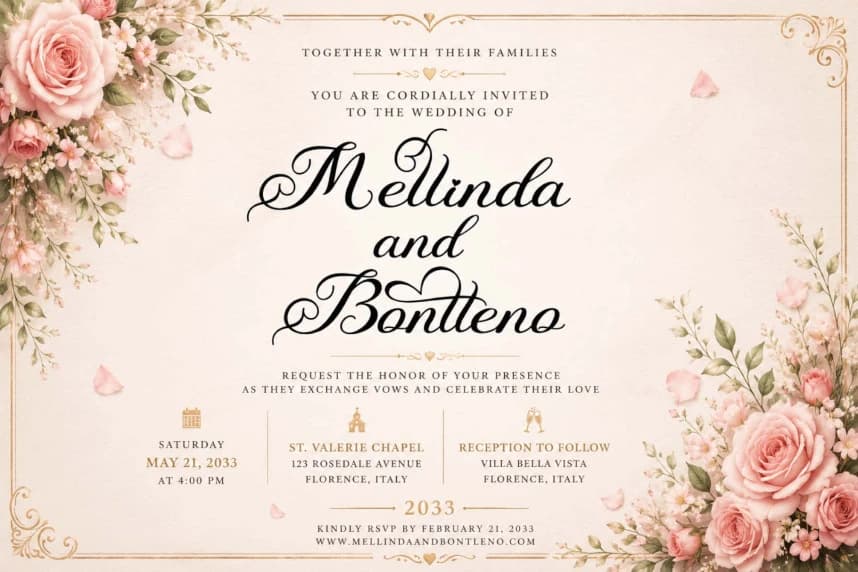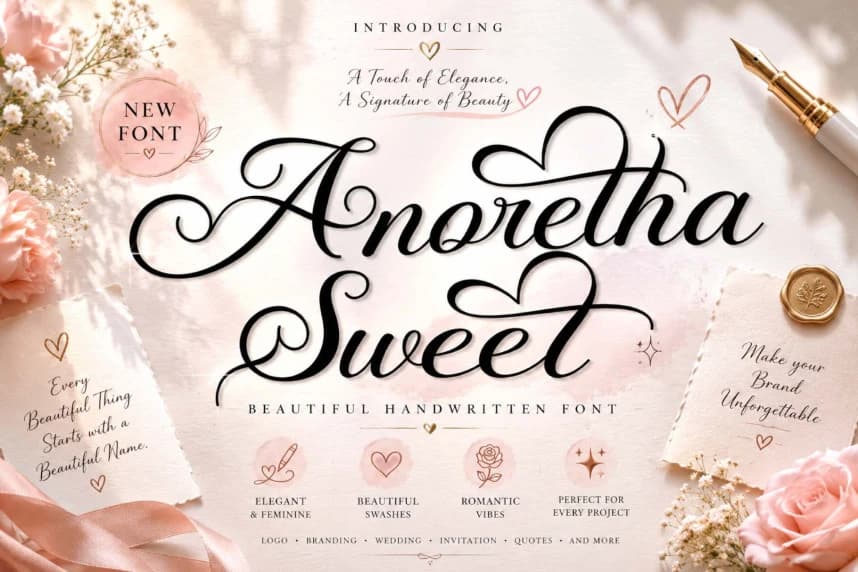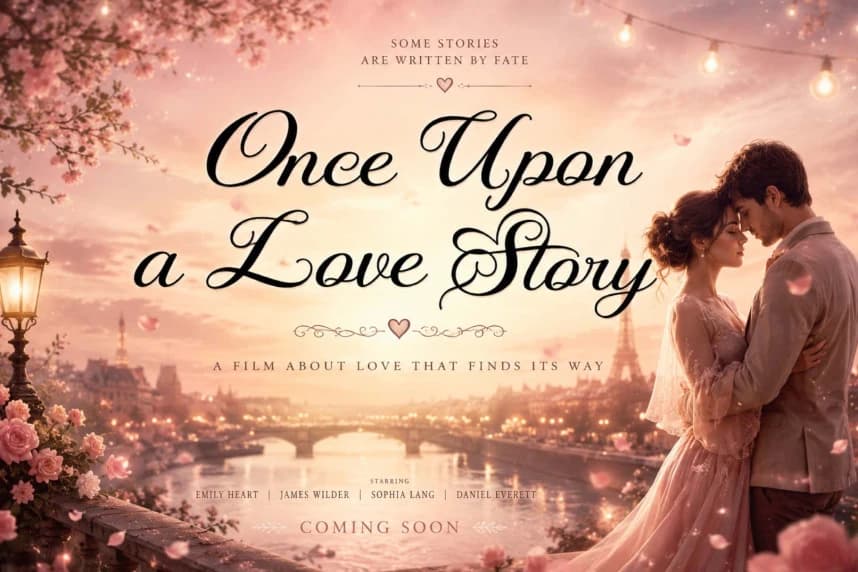
Anoretha Sweet Yazı Tipi
Anoretha Sweet zarif el yazısı fontu; Regular ve Italic stilinde. Büyük/küçük harfler, rakamlar, noktalama işaretleri, çok dilli destek ve ligatürler içerir. Kişisel kullanım lisanslı.
- Ligatürler: Harf birleşimleri desteği
- Çok dilli destek: Latin tabanlı geniş karakter seti
Kullanım Alanları
- Davetiye kartları, afişler ve başlıklar için zarif bir el yazısı görünümü
- Blog ve sosyal medya içerikleri ile marka kişiliği yaratma
- Kişisel projeler, takvimler, el ilanları
- Şık, insan el yazısı estetiği
- İki stil ile esneklik